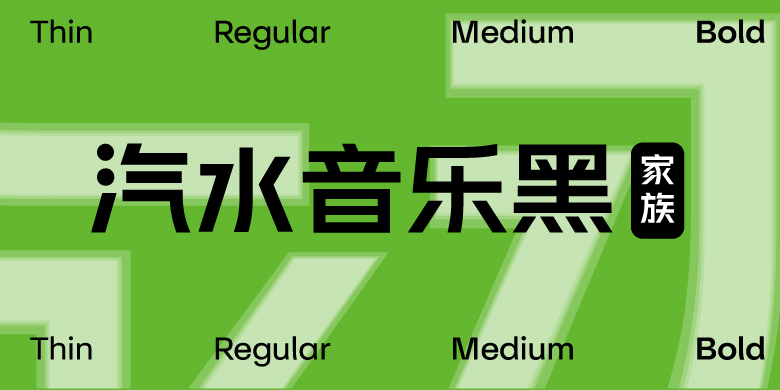
汽水音乐黑家族
汽水音乐黑体是以汽水音乐APP的品牌而命名。设计概念同样是延续“汽水”的概念出发同时结合音乐产品的属性,字形上融合气泡的形态作为汽水体的独有特征,从logo图形上提取字形风格基因。音乐的韵律感是高低动态变化的,所以在汽水音乐体上提出了“音律感”的概念。设定了一套可变的动态字体,不只是粗细的动态变化,同时加入膨胀爆炸态的可变,更加的契合不同音律的变化。